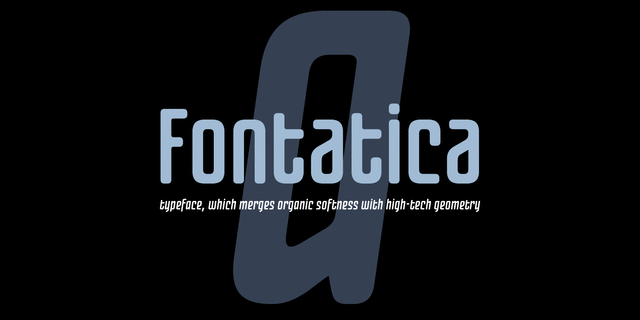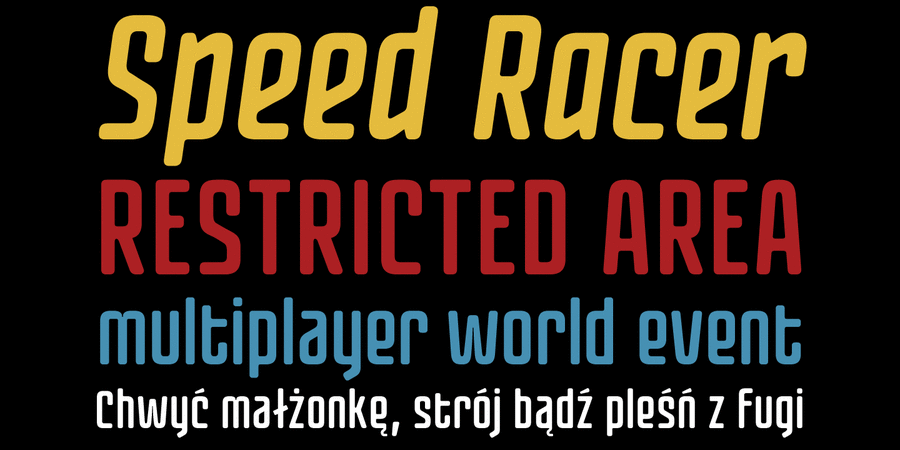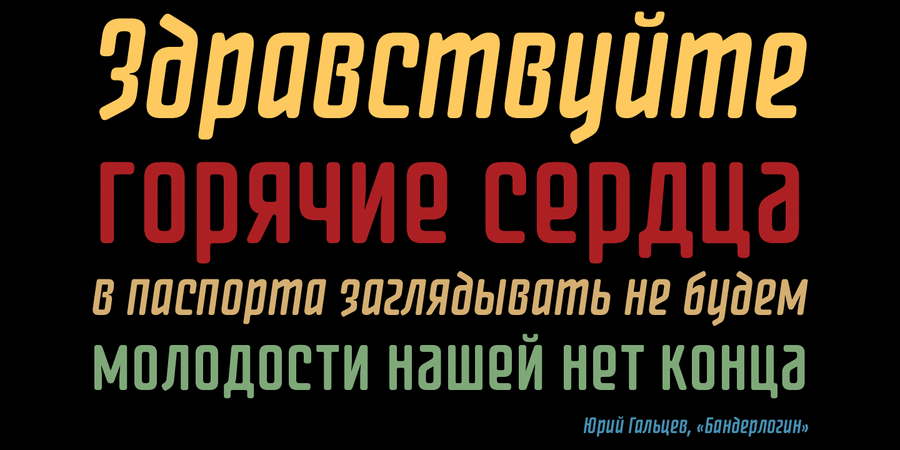
Шрифт Фонтатика сочетает технологичность с уютностью. Хорошо подходит для заголовков, плакатов и вывесок. Разработан Сергеем Ткаченко в 2012 году.
Associations for font family Fontatica 4FTypeface personality and character:
straight, technogenic, strong, serious, convincing, static, iron, reliable, manly, self-assured, steel, stable, flat, automatic, engineering, accurate, rectangular, industrial, economical, urban, smooth, tall, urbanistic, computer, experimental, tough, futuristic, neon, rubber, cinematic, friendly, pleasant, dynamic
equipment, device, sci-fi, space, mechanical engineering, metallurgy, fitness equipment, machine tool, tool, engineer, automation, industry, power station, energy industry, car, game, computer, toy, robot, cinema, science, gadget, urban studies, Shooter, action, airsoft, blockbuster, thriller, footwear, IT specialist, IT, technology, android, hardware, fuel, TV, show, x-ray, spaceship, selfie, fridge Typeface exhibits stylistic traits: